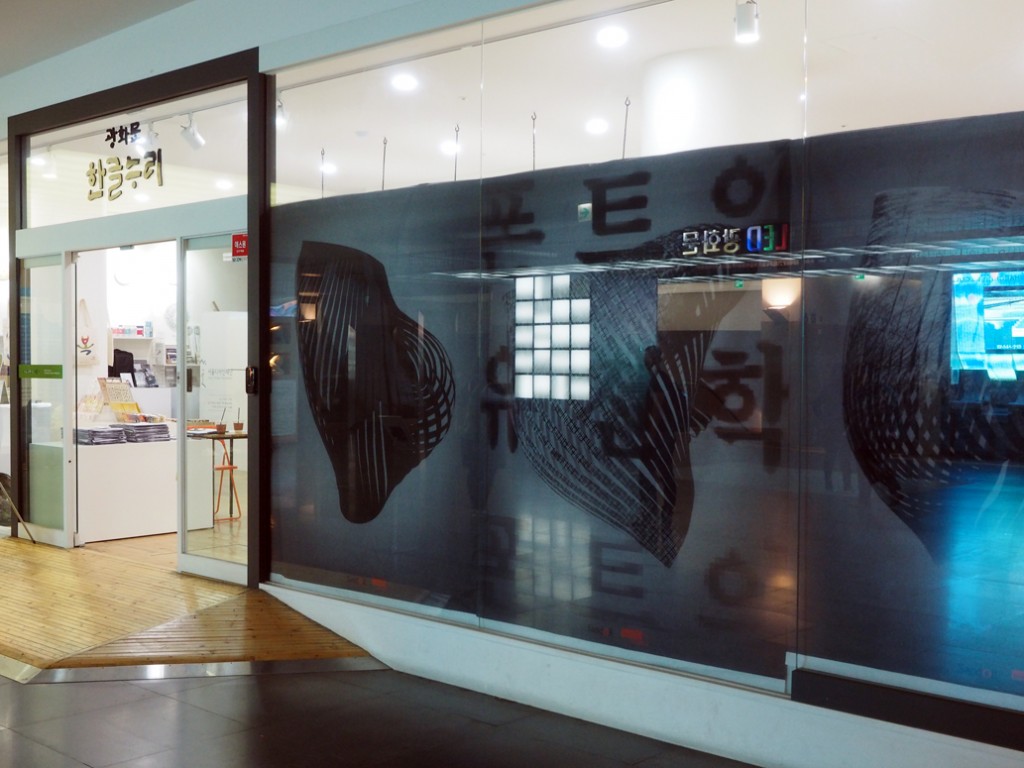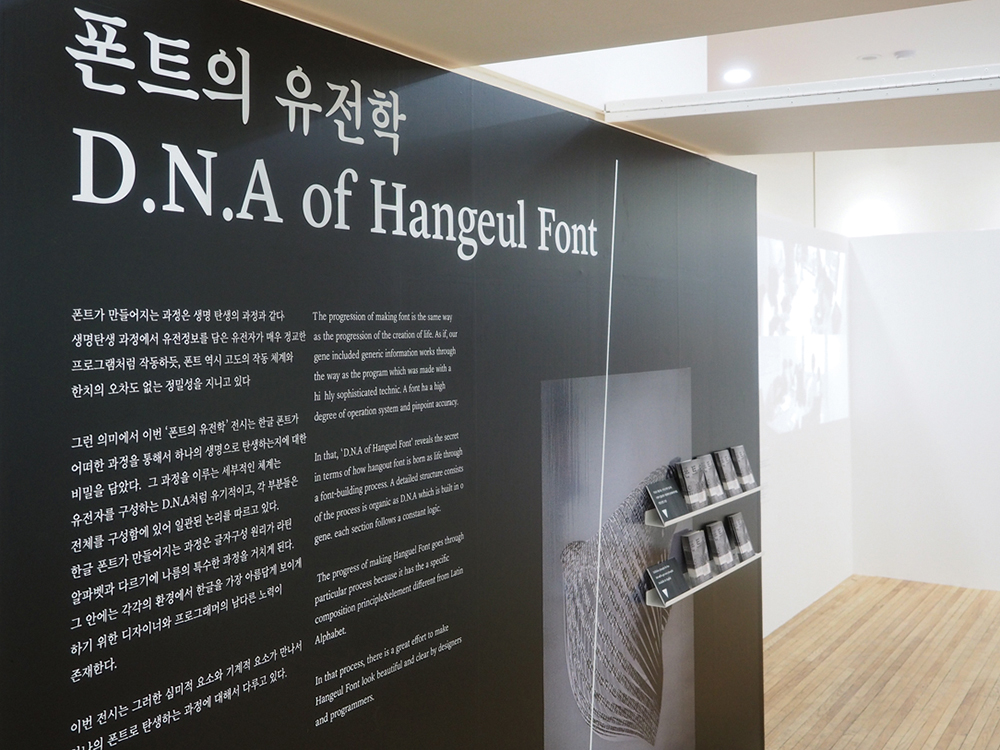
2016 한글날 기획전시 : <폰트의 유전학>
한글날을 기념하여 서체 회사 산돌커뮤니케이션이 기획 전시 <폰트의 유전학>을 진행했다. 본 전시는 하나의 한글 서체가 제작되는 과정을 토대로, 서체 제작 과정의 세부적인 체계가 사람의 유전자처럼 유기적이라는 점에 착안하여 그 과정을 생생하게 선보였다. 특히 그 과정의 중심에 있는 서체 디자이너와 개발자의 노력을 영상과 작업 과정 및 작업 공간을 구체적으로 재현하면서 관객들에게 생생하게 전달했다.
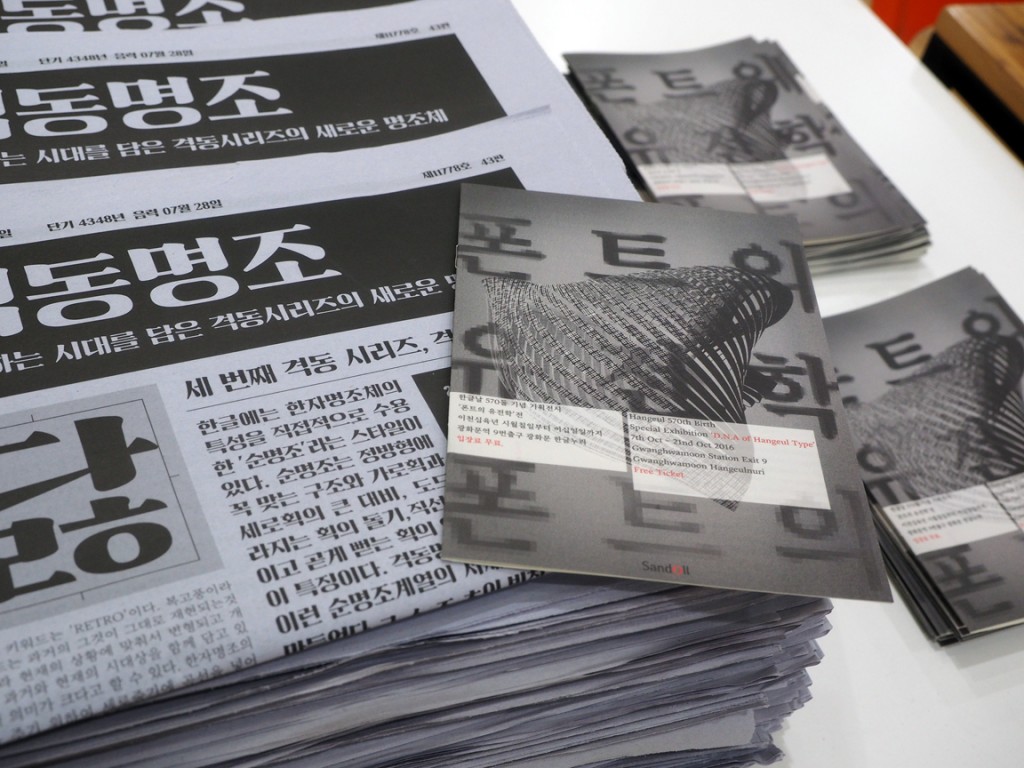
<폰트의 유전학> 전은 서체를 집합체로, 과정을 세포로 표현하여 세포 없인 집합체가 완성되지 않는다는 유전학을 토대로 각 구역을 순서대로 돌아볼 수 있게끔 구성되었다. 리서치 및 아이데이션, 디자인, 개발, 힌팅(HINTING), 출력 총 다섯 단계로 구성된 본 전시는 전문가뿐 아니라 일반 대중 역시 알기 쉽도록 섬세하고 친절하게 꾸려져 접근성을 높였다.
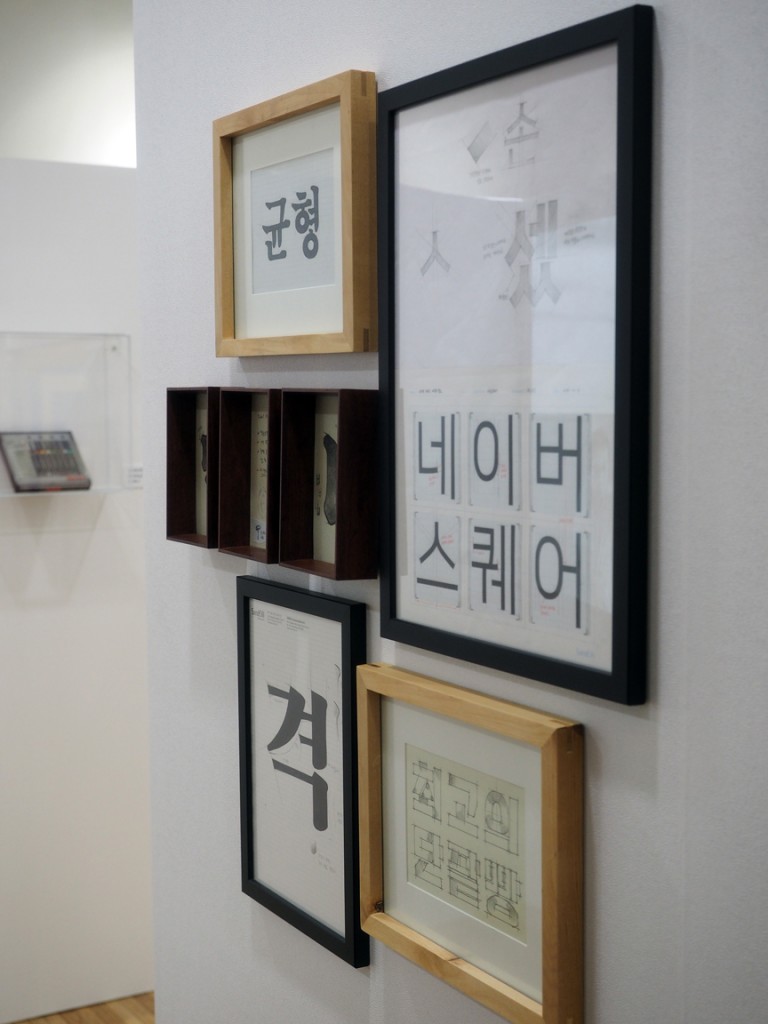
산돌은 단순히 서체의 제작 과정을 단계별로 강의하듯 전시한 것이 아니라, 디자이너의 책상을 소품까지 그대로 구현하여 보는 재미를 더했고, 재현해둔 책상 위 모니터에 디자이너의 작업 환경을 고스란히 녹화하여 마치 실제 작업 현장을 보는 듯한 기분을 자아냈다. 또한, 디자이너가 제작한 서체를 OTF, TTF 파일로 변환하는 개발자의 실제 작업 모습과 과정을 담은 영상을 송출하는 단일 공간을 꾸려, 스케치에서 시작된 서체가 어떻게 우리가 내려받을 수 있게끔 변환되는지, 그 제작 과정을 생생하게 선보였다.
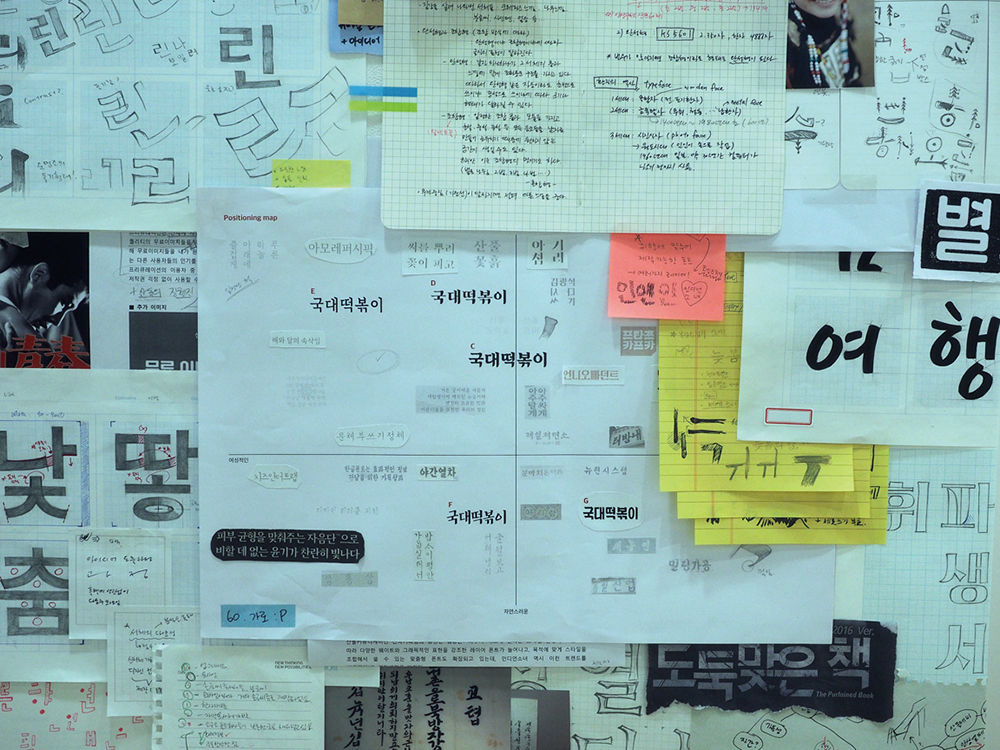
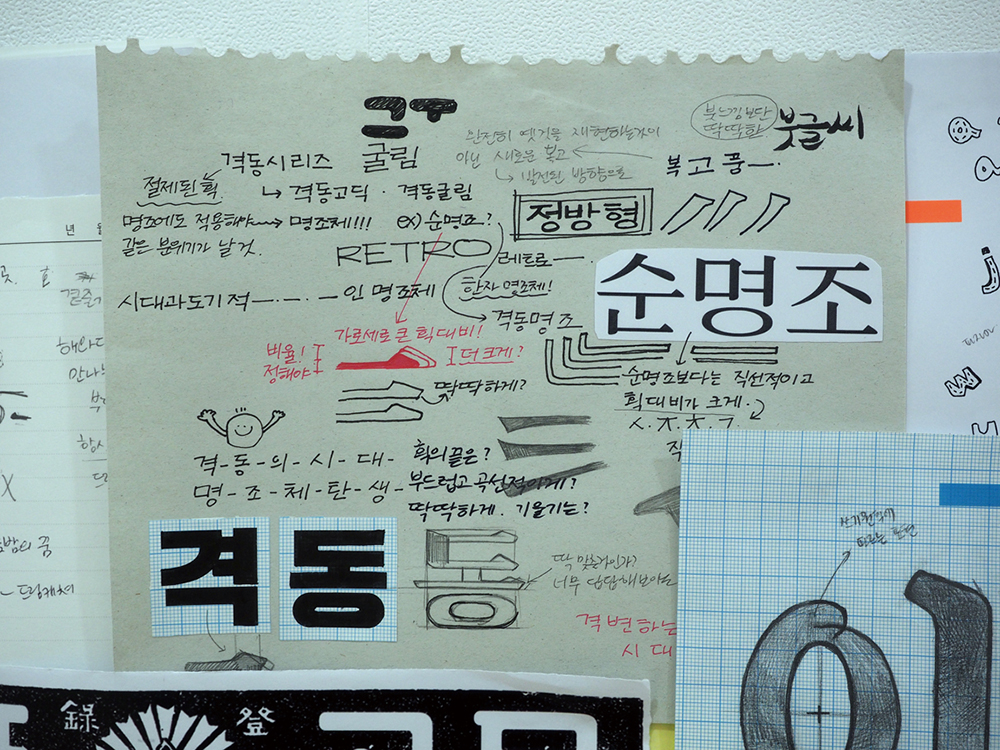
이 전시에서 가장 유용한 구역은 웹, 앱, 그리고 인쇄물로의 출력 이전에 이루어지는 힌팅 기술에 관한 전시였다. 힌팅은 지난 2004년, 기존엔 영문에만 적용되었던 기술을 국내 최초로 UI 서체였던 마이크로소프트의 맑은 고딕에 처음 적용하기 시작하면서 본격 활용된 기술로, 그 필요성이 꾸준히 대두되고 있는 단계다.
“2004년 당시에는 처음 하는 작업이다 보니 새롭고 실험적이었습니다. 맑은 고딕에 힌팅을 적용한 이후 나눔 고딕, 서울서체, LG 그룹서체, 현대카드 등 수많은 기업에서 서체를 의뢰해오면서 헌팅 기술도 함께 의뢰해오기 시작했죠. 헌팅이라는 게 저해상도에서 글자를 잘 보이게 해주는 기술이다 보니, 해상도가 좋아지면서 자연스럽게 사라질 줄 알았지만 오히려 의뢰는 점차 증가하더라고요. 좀 더 나은 사용자 환경을 위해 힌팅도 같이 발전하고 있는 것 같아요.” 커머셜폰트팀의 최성우 팀장이 말한다.